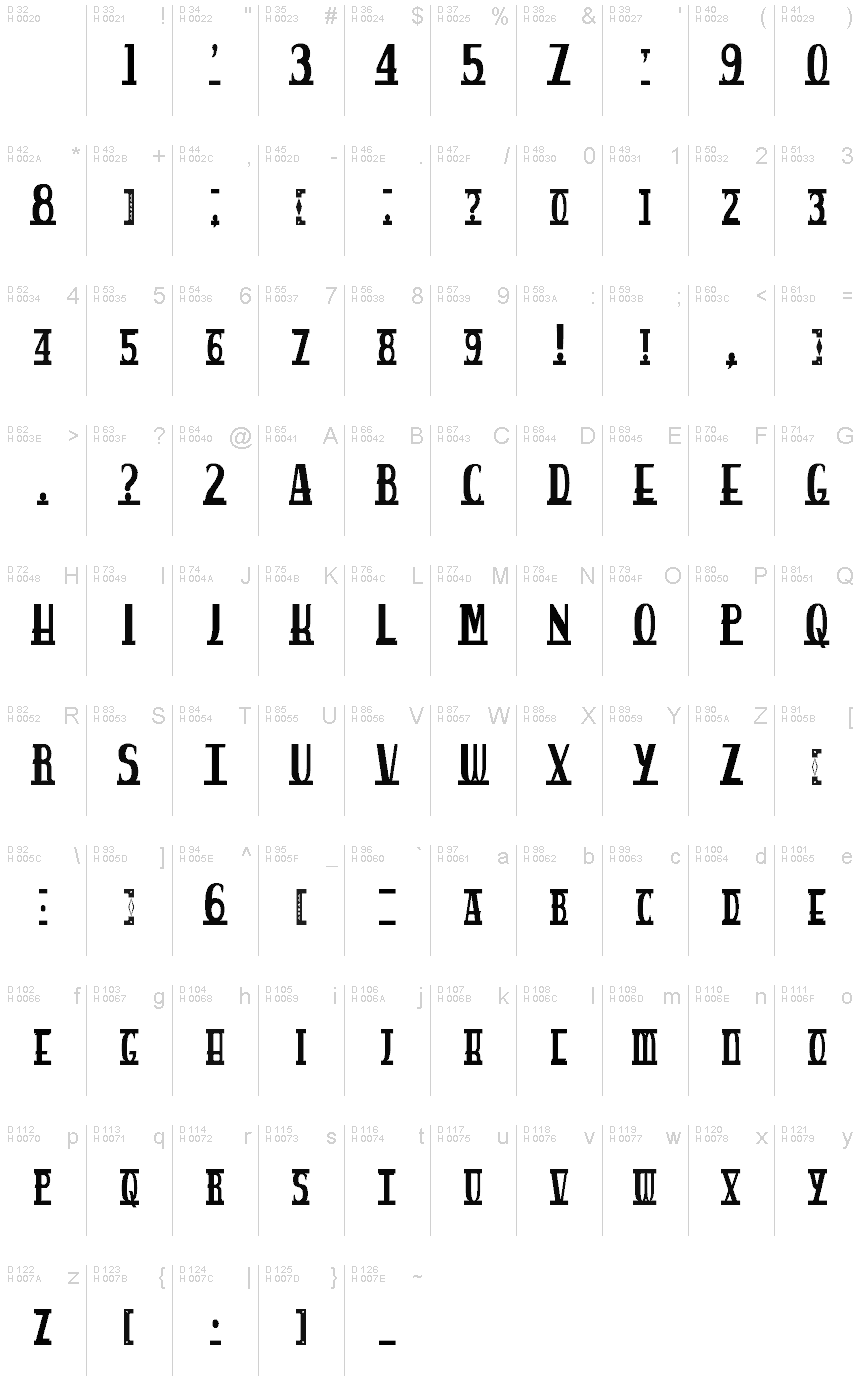
spankys bungalow
Spankys Bungalow è un font display distintivo realizzato da Emerald City Fontwerks, che emana un fascino Western ruvido e autentico. La sua larghezza condensata ne esalta la presenza d'impatto, rendendolo la scelta ideale per progetti che richiedono attenzione con un tocco di nostalgia. I caratteri stilizzati vantano linee decise e grazie giocose che richiamano la cartellonistica vintage e il classico stile Americana.
Il fascino estetico di Spankys Bungalow risiede nella capacità di trasportare chi guarda nell'era dei vecchi western, mantenendo al contempo una sensibilità di design moderna. Questo font non è solo una scelta tipografica, ma uno strumento evocativo in grado di dare il tono a svariati progetti creativi, dagli inviti a eventi a tema ai poster più accattivanti.
Che tu voglia catturare l'essenza della frontiera o semplicemente aggiungere carattere ai tuoi progetti di branding, Spankys Bungalow è pronto a fare la differenza con il suo stile unico e la sua composizione condensata.